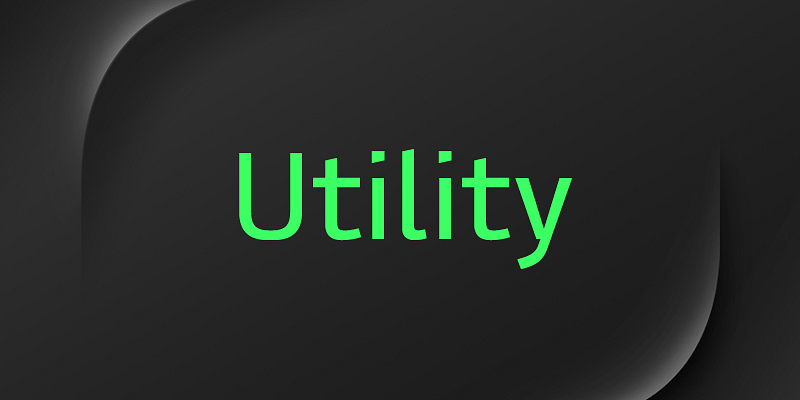
Utility Pro Font
Utility Pro Font là một lựa chọn được ưa chuộng trong các thiết kế hiện đại nhờ vào sự cân bằng giữa tính thẩm mỹ và tính thực dụng. Đây là một font chữ sans-serif với các đường nét gọn gàng, rõ ràng, mang lại cảm giác chuyên nghiệp và dễ đọc. Utility Pro Font thuộc bộ font chữ không chân, thường được sử dụng trong các dự án thiết kế web, đồ họa và in ấn, nơi mà sự rõ ràng và dễ đọc là yếu tố quan trọng. Với khả năng linh hoạt cao, font chữ này có thể được áp dụng trong nhiều ngữ cảnh khác nhau, từ nội dung chính văn bản đến các tiêu đề, mang lại vẻ ngoài tối giản nhưng không kém phần tinh tế.